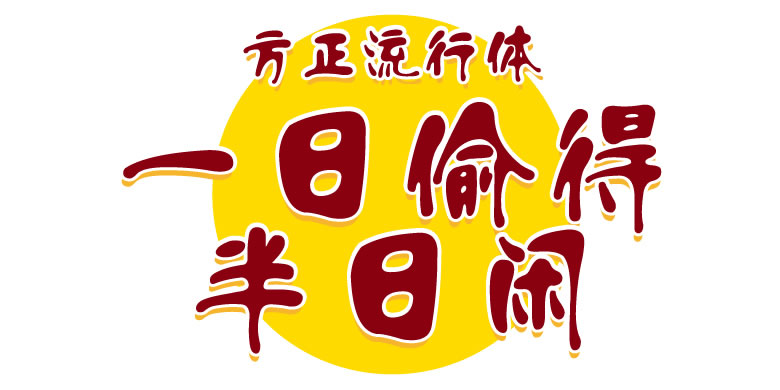
品牌:方正字库设计师:苏英华发行时间:2003字库编码:大陆简体(GB2312-80)、大陆繁体(GB12345-90)、简繁扩展(GBK)分类:创意字体
方正流行体以带有流动感的笔触设计而成。其笔画带有手写的意味,横向笔画左细右粗,竖向笔画上粗下细,笔画间相互融合,流畅舒展富有动感。方正流行体的个性奔放有活力,适用于生活类品牌的广告和产品包装设计。